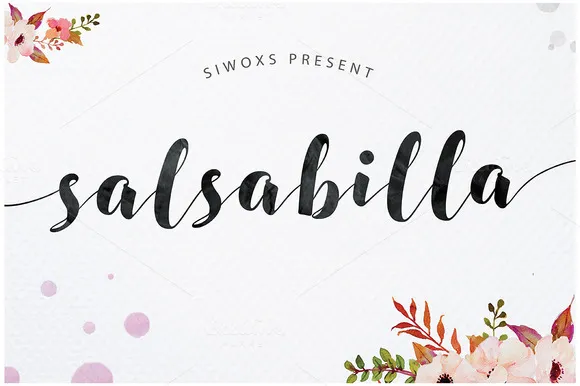
Salsabilla é uma fonte tipográfica de calligrafia que traz com ela uma sensação suave e fluida, combinando elementos modernos com um toque ondulado característico. Esta opção de letra moderna foi projetada para atender às necessidades dos designers em busca de novas ideias para seus próximos trabalhos gráficos. Salsabilla é versátil e pode ser usada em uma ampla variedade de aplicações, desde títulos e logotipos até cartas pessoais, convites de casamento, materiais de identificação corporativa, sinalização, rótulos, newsletters, fitas de cor, adesivos, camisas personalizadas e muito mais. Inspirada na arte da calligrafia e no equilíbrio entre antiguidade e modernidade, Salsabilla é uma escolha perfeita para qualquer projeto gráfico que desejávamos dar um toque único e elegante.